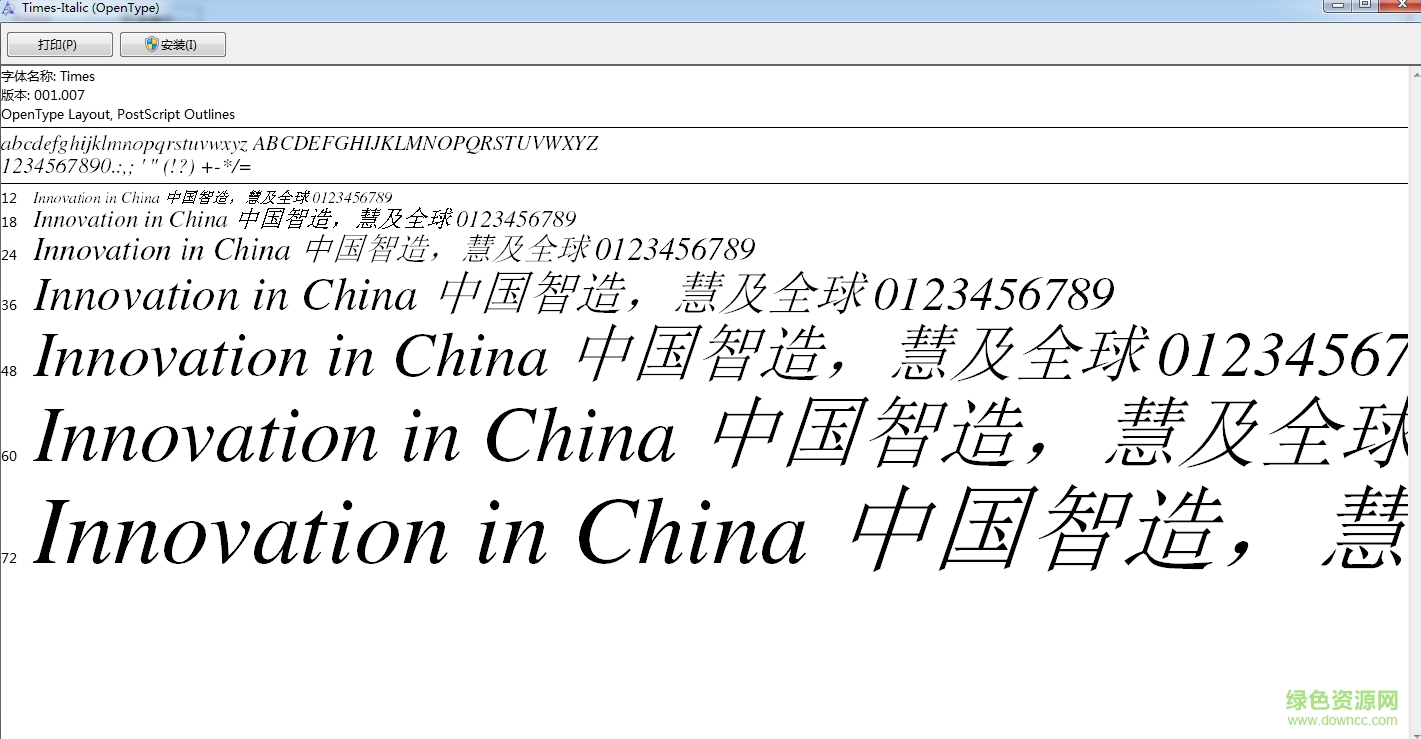
times italic字體是一款斜體樣式的英文字體,該字體點(diǎn)畫精致,線條靈動(dòng),雖然每個(gè)字都像右傾斜卻又不失穩(wěn)定,美觀與實(shí)用性兼?zhèn)?,有需要者歡迎在綠色資源網(wǎng)下載!
中文術(shù)語“斜體”是針對“正體”而言的,但作為西文字體的譯名,常被指代為“意大利體”(Italic Type)。
西文中有兩種形狀傾斜的字體:oblique type和 Italic type,
傾斜后字形也發(fā)生的變化的是“意大利體”(Italic Type),
而單純將原字體向右傾斜而沒有形變的稱為偽斜體(Oblique Type)。